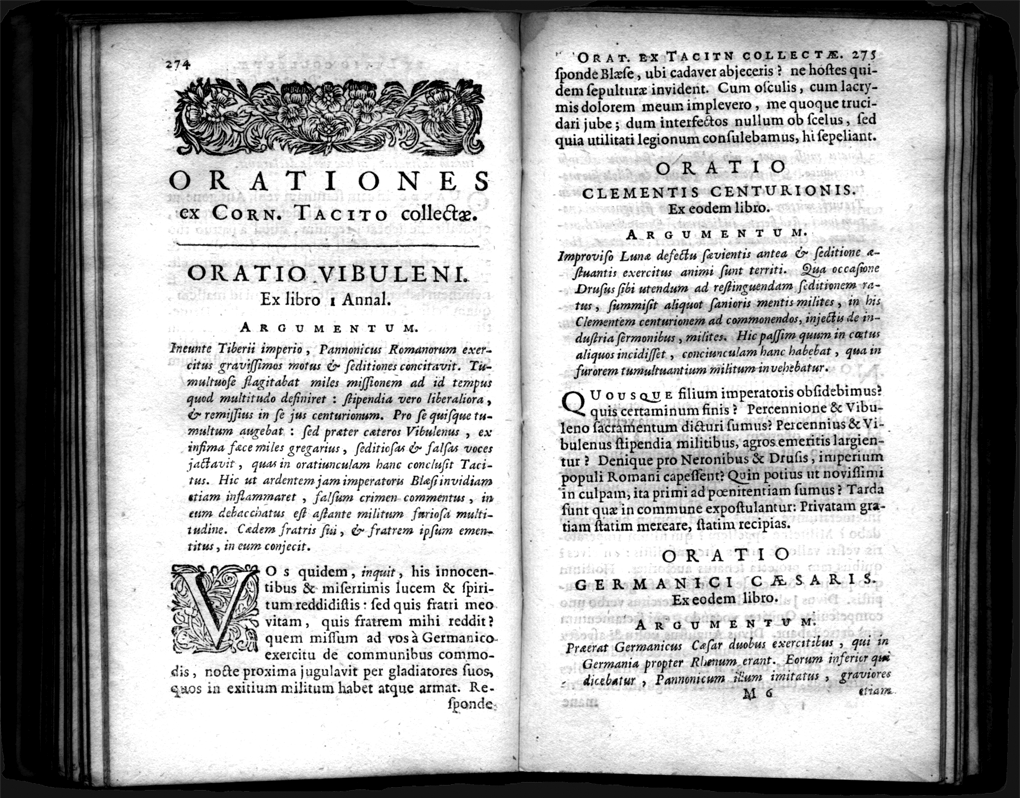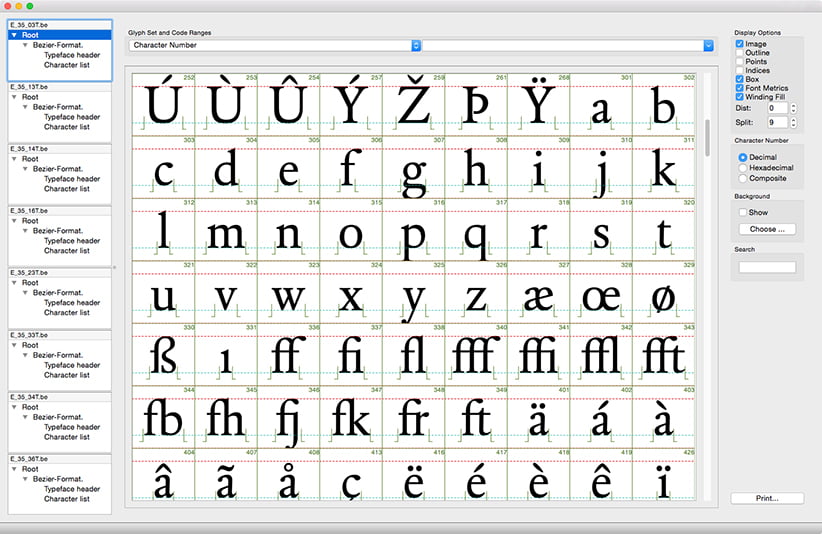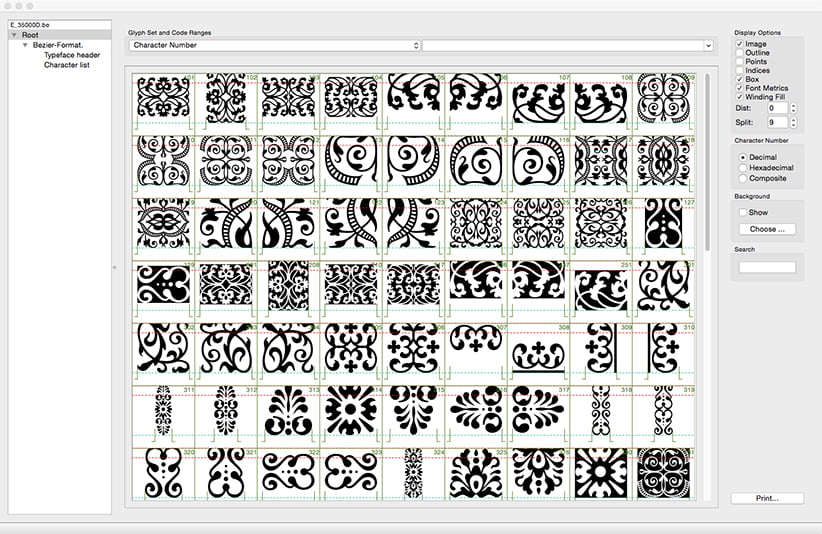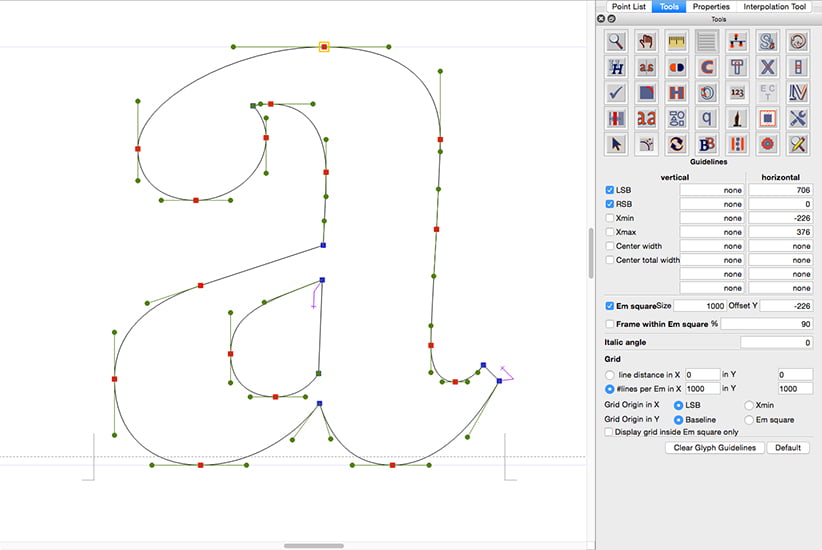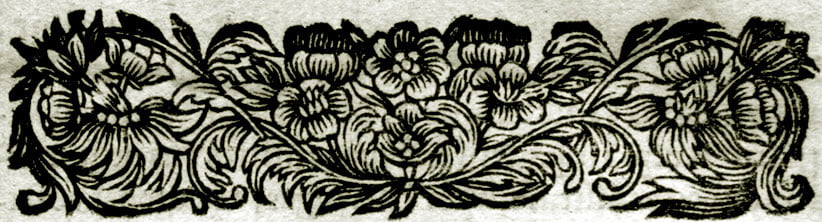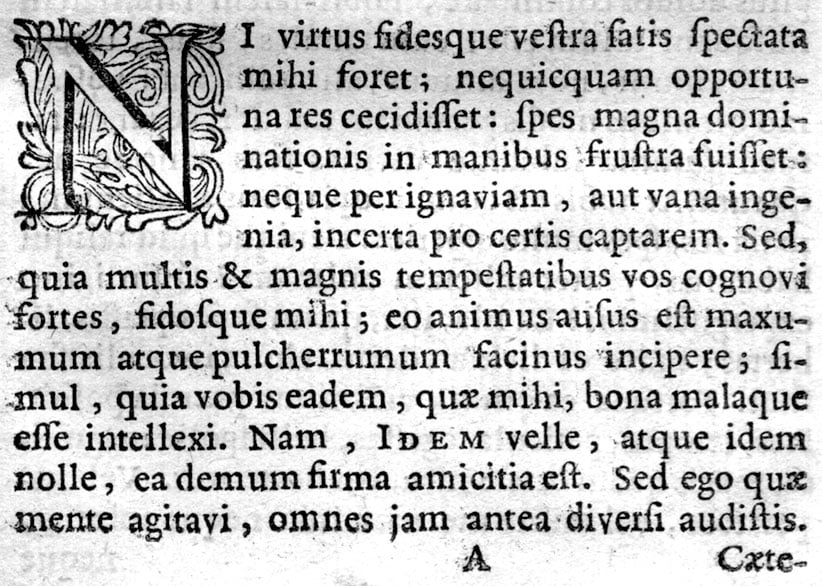
De benaming Elsevierstype of Elzévirien, waarmee iedere zetter en drukker ongetwijfeld vertrouwd is, stamt uit het einde van de achttiende eeuw. De benaming wordt gebruikt voor lettertypen die lijken op de letters die in de zeventiende eeuw werden toegepast door de beroemde drukkersfirma Elsevier. De lettertypen die de compacte typografie in de Elsevier-uitgaven mogelijk maakten, waren van de hand van Christoffel van Dijck. Deze goudsmid, stempelsnijder en lettergieter werd in 1605 in Maastricht geboren en overleed in 1670 te Amsterdam, waar hij vanaf 1648 woonde en werkte. Van Dijck heeft de reputatie de beste stempelsnijder van zijn tijd te zijn geweest. Van het œuvre van Christoffel van Dijck is niet veel meer dan de afdrukken van zijn letters bewaard gebleven. De loden letters, matrijzen en stempels van Van Dijck waren in de loop der jaren, door de overname van inboedels van verschillende gieterijen, in het bezit gekomen van de firma Enschedé in Haarlem. Mede door de populariteit van de lettertypen van Johann Michael Fleischmann raakte het œuvre van Christoffel van Dijck in de tweede helft van de achttiende eeuw uit de mode. Aan het begin van de negentiende eeuw verdween dan ook bijna al het door Van Dijck vervaardigde materiaal in de smeltkroes, om daarna dienst te doen als grondstof voor nieuw te gieten letters. In 1992 gaf de Dutch Type Library aan de letterontwerper Gerard Daniëls de opdracht voor het maken van een revival op basis van het werk van Christoffel van Dijck. Het uitgangspunt was om een uitgebreide familie te maken, onder meer met verschillende gewichten (vetheden) en met ornamenten en swashes. Gerard Daniëls onderzocht oude drukken en op basis van verschillende aan Van Dijck toegeschreven lettertypen (re)construeerde hij dtl Elzevir. De Augustijn Romeyn, die in de beroemde letterproef uit 1681 van de weduwe van Daniël Elsevier is afgebeeld, stond model voor de romein van dtl Elzevir. dtl Elzevir levert, net zoals het originele materiaal van Christoffel van Dijck, uitermate compact en gelijkmatig zetwerk op en is hierdoor bijzonder geschikt voor boekproducties. |